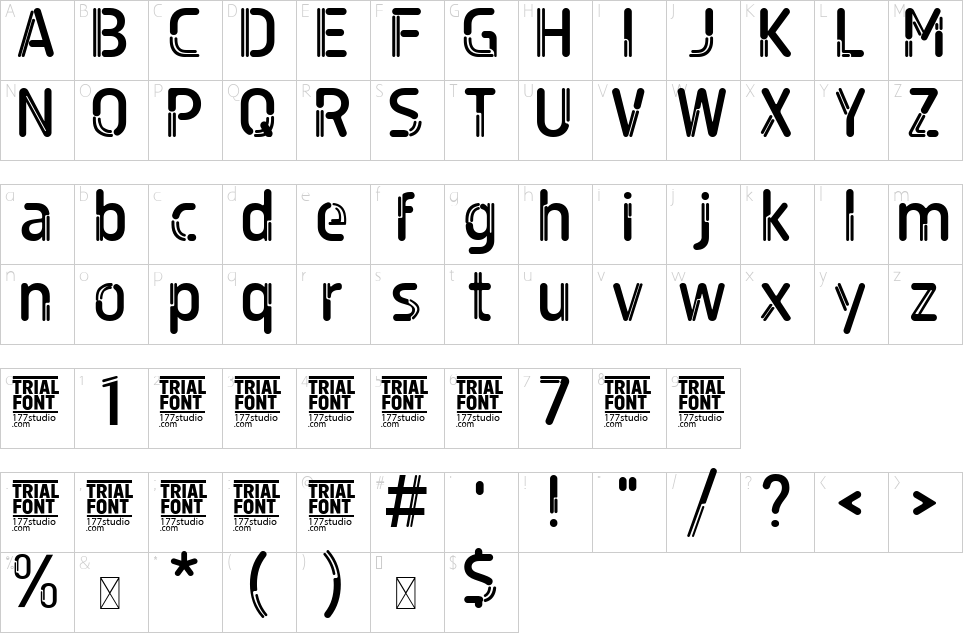
A “Daesang Space Font” é uma nova adição à biblioteca gratuita de fontes disponíveis para designers e criativos, oferecida pela 177Studio.com. Desenvolvida pensando nos requisitos estéticos de diversos projetos digitais, esta fonte garante um equilíbrio entre simplicidade e elegância, tornando-a uma escolha inteligente tanto para editoriais como para design gráfico em nível profissional. Desenvolvida especialmente para atender a um público vasto, não importa se você está trabalhando com redes sociais ou criações digitais de nível avançado, esta fonte oferece os recursos precisos necessários para personalizar seu trabalho e garantir que ele seja reconhecível por sua qualidade. Com o download da “Daesang Space Font”, designers podem adicionar um toque moderno e sofisticado a seus projetos digitais de forma gratuita. Esta elegante fonte é uma excelente opção para aqueles buscando diversificar seu portfólio com uma solução gráfica sólida e funcional, sem precisar recorrer a versões pagas que podem ser restritivas ou caras.